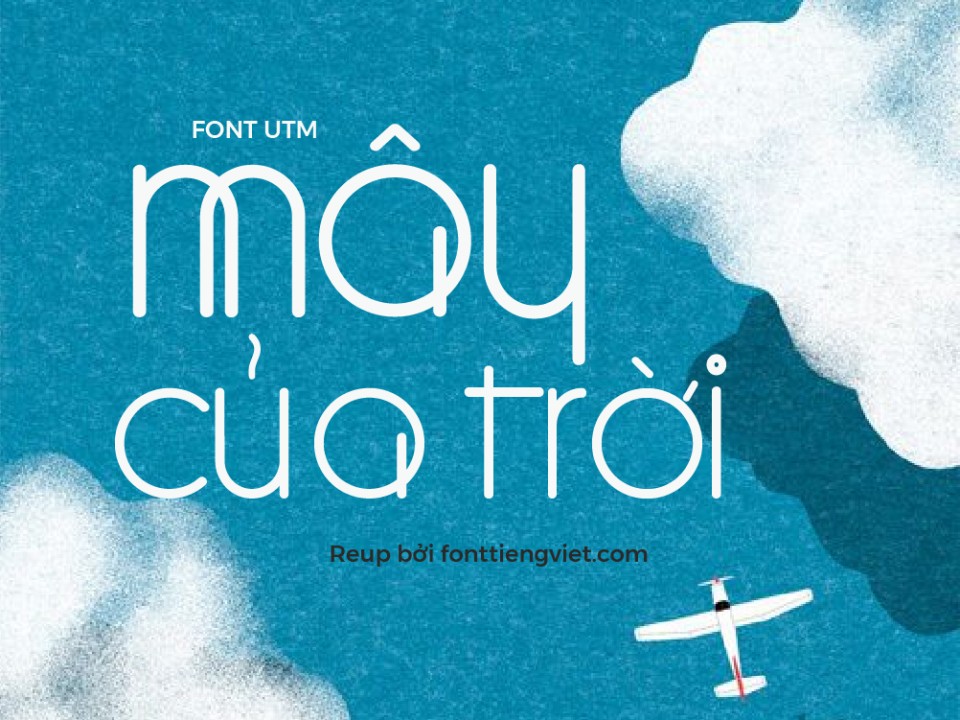
Font việt hóa UTM Soraya
Giới thiệu về Font việt hóa UTM Soraya trong thiết kế
Trong thế giới đồ họa, việc lựa chọn một Font Miễn Phí chất lượng luôn là ưu tiên hàng đầu của các nhà sáng tạo. Font việt hóa UTM Soraya là một trong những bộ phông chữ thuộc hệ thống UTM (Unicode Typeface Metadata) nổi tiếng tại Việt Nam. Với những đường nét thanh mảnh, hiện đại nhưng không kém phần sang trọng, bộ chữ này đã trở thành công cụ đắc lực cho nhiều dự án truyền thông khác nhau. Đặc biệt, nhờ được việt hóa hoàn chỉnh, người dùng có thể thoải mái gõ tiếng Việt mà không lo lỗi hiển thị hay mất ký tự đặc biệt.
Đặc điểm nổi bật của Font việt hóa UTM Soraya
Phong cách thiết kế thanh lịch
Font việt hóa UTM Soraya sở hữu cấu trúc chữ cân đối với các nét cong mềm mại. Điều này tạo nên cảm giác dễ chịu cho mắt người đọc, phù hợp để trình bày nội dung văn bản dài hoặc các tiêu đề cần sự tinh tế. Sự kết hợp giữa nét truyền thống và hơi thở hiện đại giúp Soraya không bị lỗi thời qua nhiều năm tháng sử dụng.
Tính ứng dụng linh hoạt trong đời sống
Bộ phông này cực kỳ phổ biến trong các thiết kế thiệp cưới, bìa sách, poster quảng cáo và cả giao diện website. Trong môi trường học đường, các bạn học sinh và giáo viên thường xuyên sử dụng Font việt hóa UTM Soraya để làm bài thuyết trình PowerPoint thêm phần sinh động. Độ tương phản giữa các nét chữ giúp thông tin được truyền tải một cách rõ ràng và ấn tượng nhất.